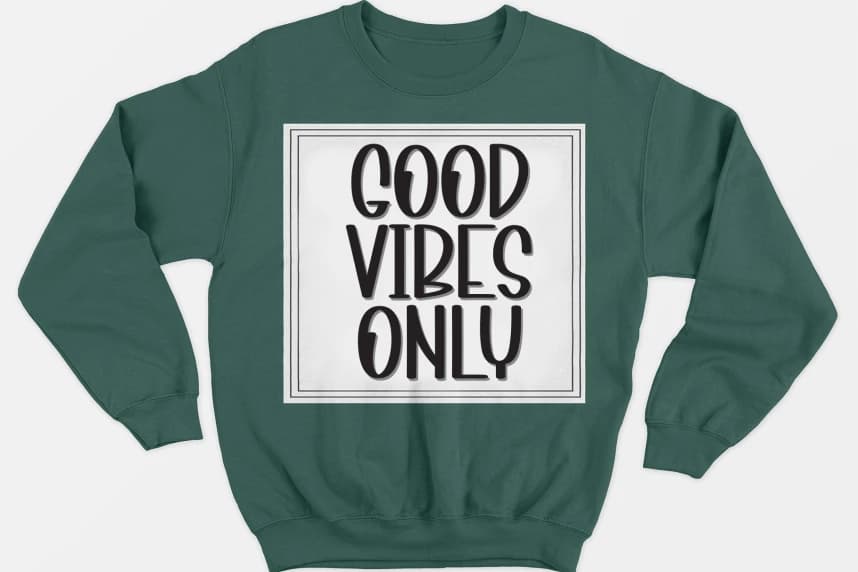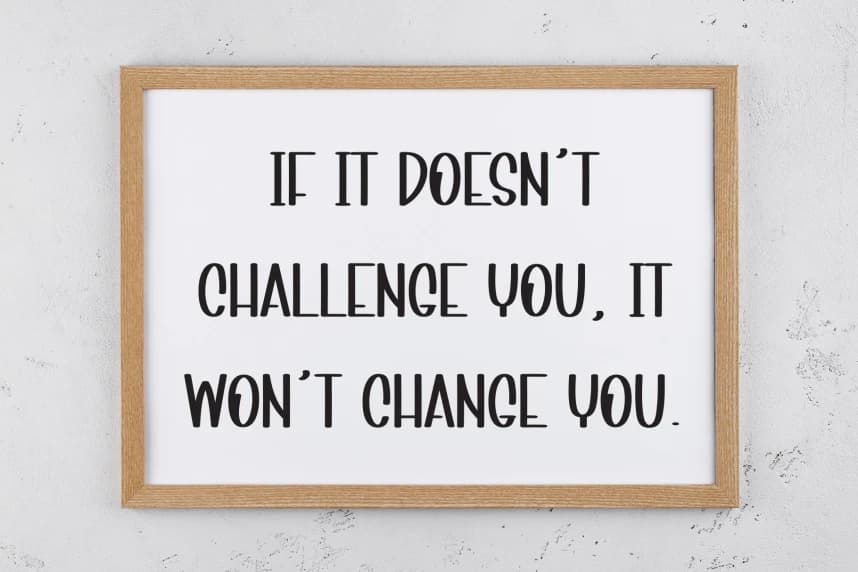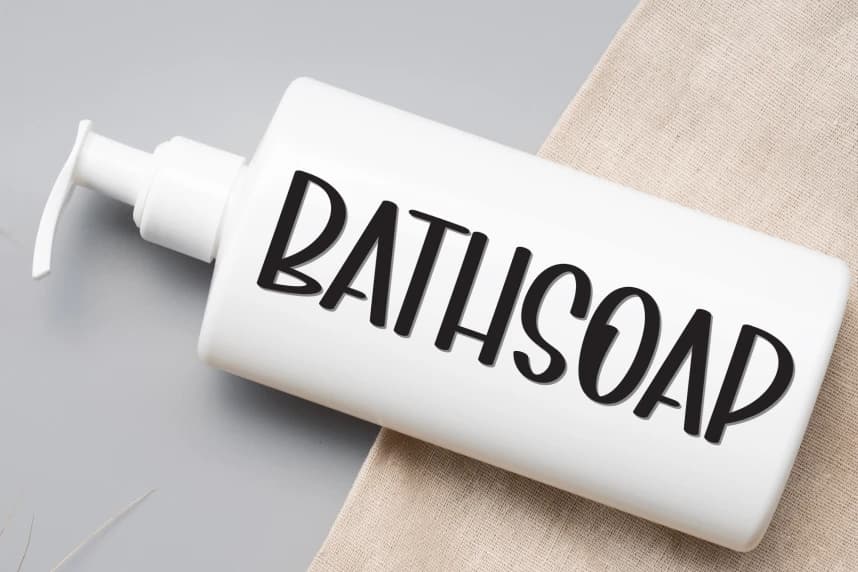
Magic Summer El Yapımı Yazı Tipi
Magic Summer Handcrafted Font, tatlı ve dostça bir el yazısı stilinde gösterim yazı tipidir. Sevimli ve eğlenceli olan bu font, düğün davetiyelerini, kartları yazmak için veya eğlenceli bir dokunuşa ihtiyaç duyabilecek diğer tüm tasarımlar için idealdir!
Magic Summer Handcrafted Font, tatlı ve dostça bir el yazısı gösterim yazı tipidir. Sevimli ve eğlenceli olan bu yazı tipi, düğün davetiyelerini, kartları yazmak için veya oyuncu bir dokunuşa ihtiyaç duyabilecek herhangi bir tasarım için idealdir!